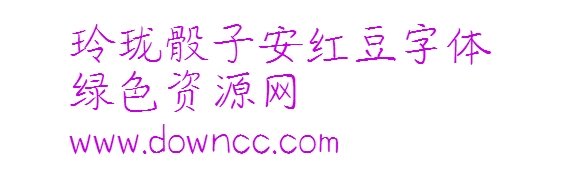
玲珑骰子安红豆ttf字体是一款有着清婉秀气古色韵味的手写字体,无论是中文还是英文都有着舒缓工整的造型,给你极佳的阅读体验,喜欢本字体的朋友就可以来绿色资源网免费下载哦!
玲珑骰子安红豆字体是手机qq上使用的唯美艺术字体,字体细致婉约如同诉说着绵绵情意,造型疏松而不压抑,具有很高的文字辨识度,可以适用于印刷排版、海报设计、创意广告等领域。